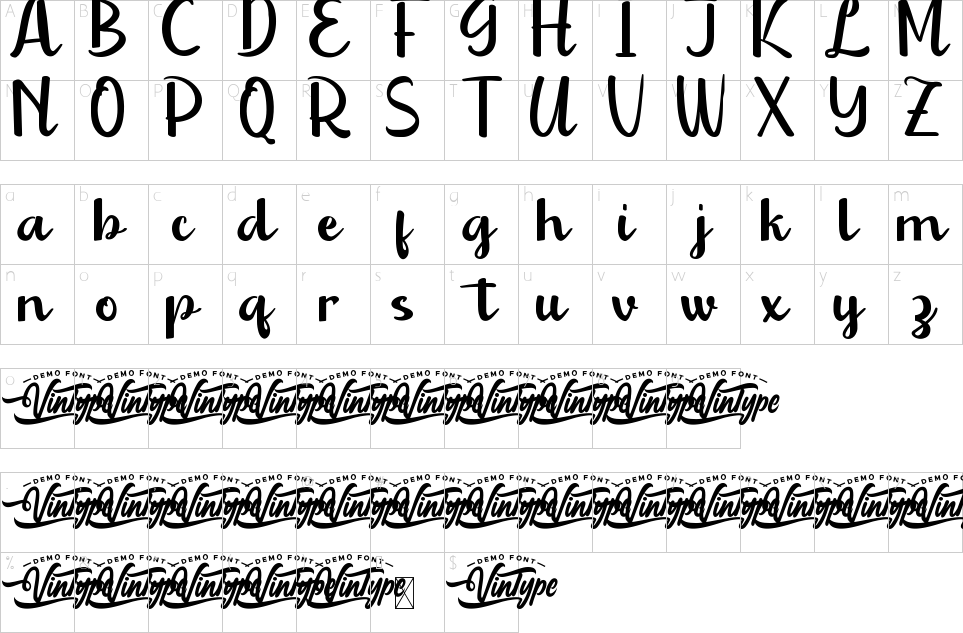
Descubra a Aesthetic Love, uma fonte de graça que transmite um amor pelo bom gosto e elegância. Desenvolvida por VinType, esta fonte é perfeita para aqueles que valorizam a beleza minimalista e sofisticada. Com suas linhas leves e sua paleta de cores suave, Aesthetic Love é perfeita para criar designs que encantam. Esta fonte foi projetada para ser não apenas usada, mas para ser amada. Seja para gráficos digitais ou para criações de papel, Aesthetic Love oferece o equilíbrio perfeito entre modernidade e elegância. Sua simplicidade faz dela uma escolha ideal para qualquer projeto que busque transmitir um toque delicado de estilo. Aesthetic Love é mais do que uma fonte; ela é uma experiência de design. Baixe-a agora e descubra por si mesmo o encanto dessa fonte única.